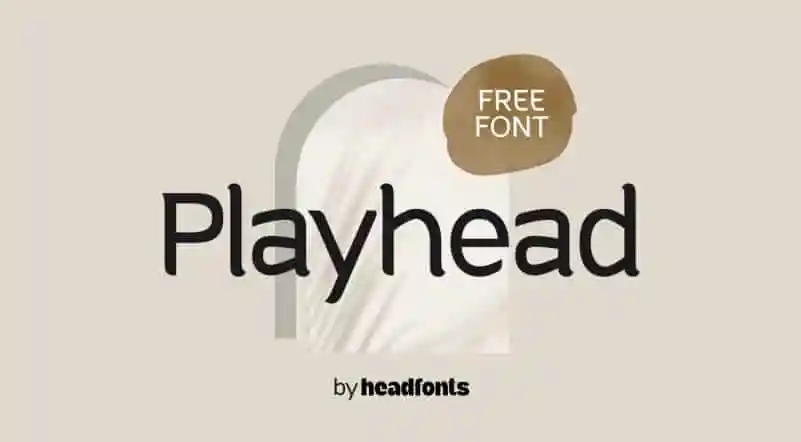
Introduzimos a Playhead Serif Font – uma font séria elegante com traços de tipo serifa, que traz um toque divertido sem perder sua classe. Com suas curvas intrigantes, a Playhead Serif mantém seu charme atraente e estável para qualquer projeto criativo. Esta fonte vem em três pesos: Regular, que é gratuita, e duas alternativas mais grossas, Bold e Extrabold. A Playhead foi projetada para ser versátil, natural e com um toque alegre, razão pela qual seus caracteres têm ângulos arredondados e uma pequena serif decorativa que imita os traços de uma pena. A Playhead tem letras maiúsculas e minúsculas, com 63 glífer por cada fonte e suporte para o script latino padrão, incluindo números. Esta fonte perfeitamente combina com títulos de filmes, logotipos, blogs, identidades corporativas, títulos de livros, redes sociais, cartas de casamento ou simplesmente em qualquer projeto de design. A Playhead é perfeita para muitas ocasiões e está aí para enriquecer seu próximo trabalho gráfico.